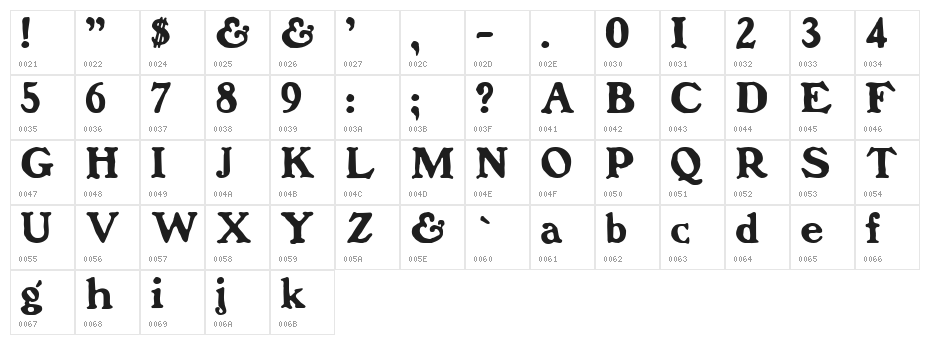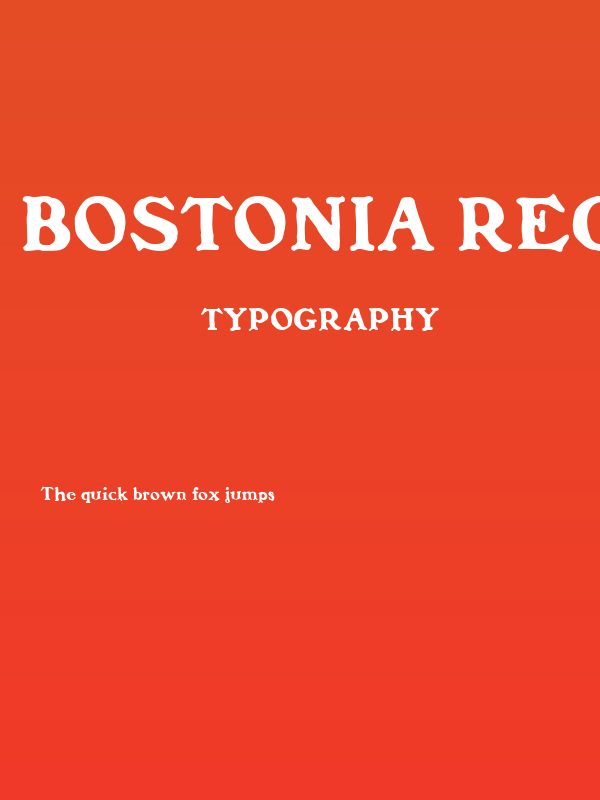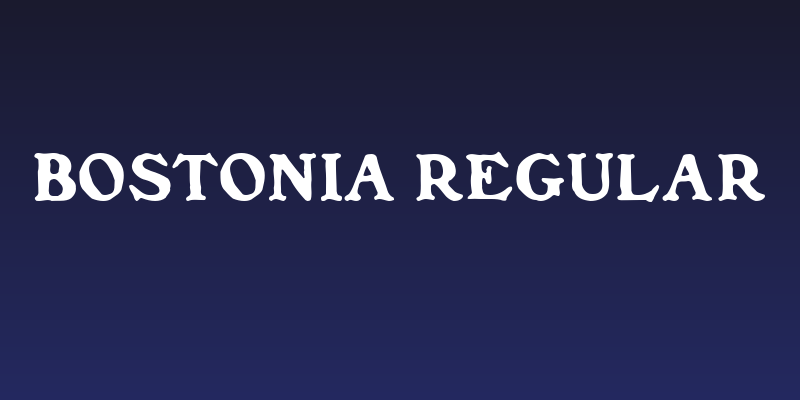
Bostonia Regular Font
| Gesamtstil | Vintage |
| Vorgeschlagene Projekte | Ideal for vintage-themed posters, branding, book covers, and any project seeking a classic, old-world aesthetic. |